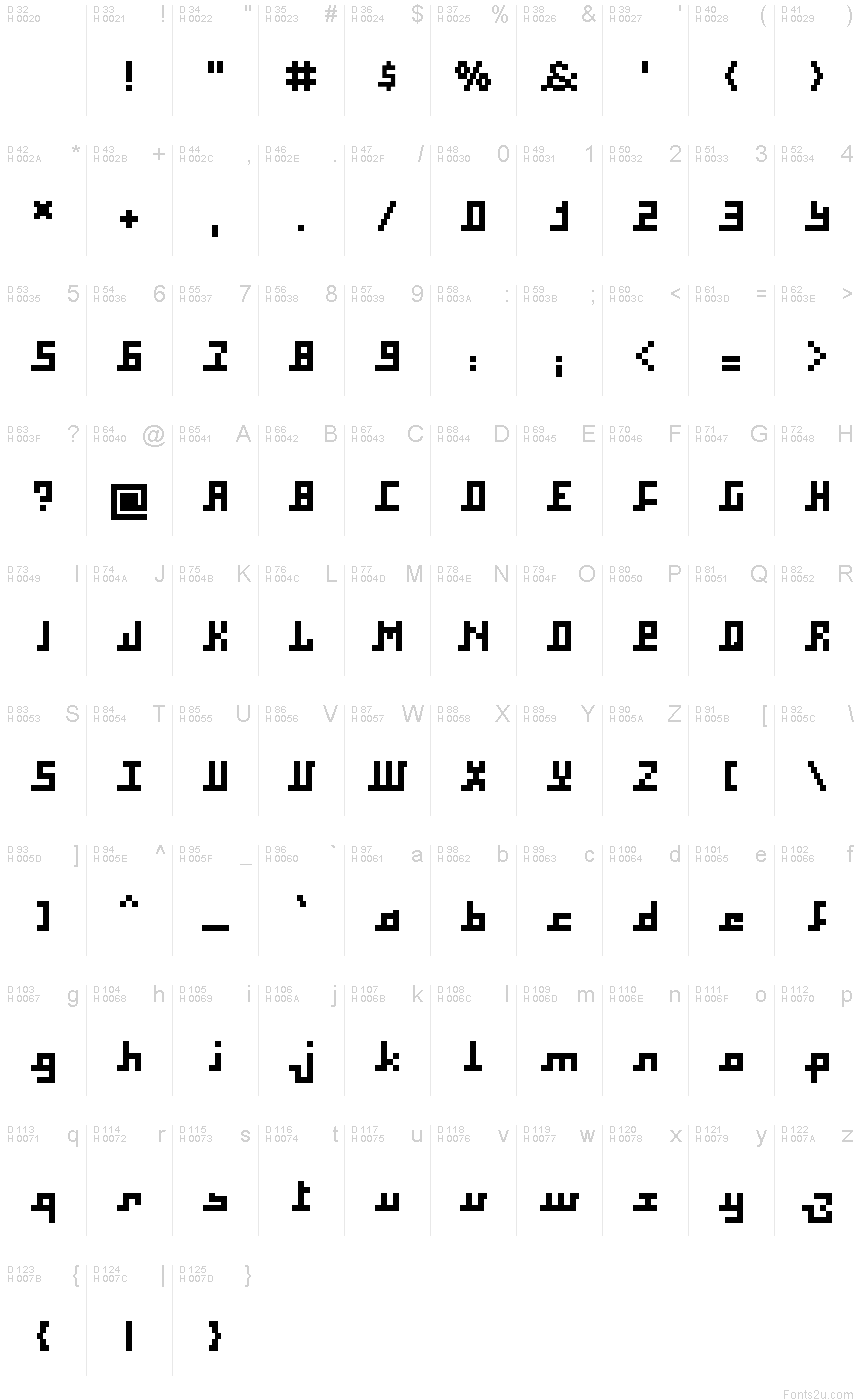
Square Bold ist ein kostenloser Bitmap-Pixel-Font mit dem kantigen, stufenartigen Look früher Bildschirmgrafiken. Die Buchstaben bestehen aus massiven, quadratischen Modulen und langen horizontalen Linien, was der Schrift einen flachen, an Retro-Spiele erinnernden Rhythmus verleiht – simpel, blockig und mit Ecken und Kanten.
Sie passt perfekt zu Retro-Gaming-Branding, Zine-Überschriften, Plakattiteln, Splash-Screens und kompakten Logo-Ideen, bei denen die gitterartige Textur den Ton angibt. Als kostenlose Schrift eignet sie sich zudem hervorragend für kurze Interface-Beschriftungen, Titelkarten und andere kleine Anzeigebereiche, die von ihrem harten, niedrig aufgelösten Charakter profitieren.